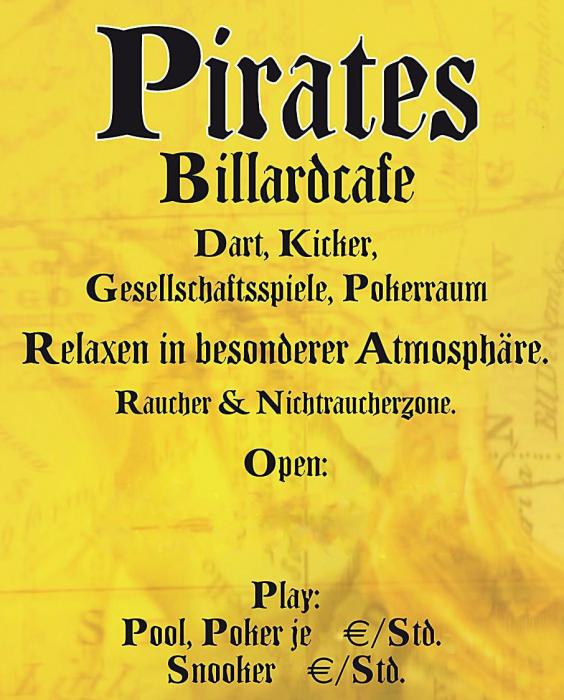
Suche verschörkelte Schriftart -
Habe schon einige Schriftart Seiten ausprobiert,
aber keine konnte genau oder auch nur annähernd
diese Schriftart identifizieren.
Brauche diese um die Getränkekarte umzuändern.
Die Kleinbuchstaben: Ein Freefont namens "BlendfontsMultikultur"
Die Großbuchstaben: Arrus Blk
Du musst nur die beiden verwendeten Schriften trennen, dann werden sie auch erkannt. Also "irates" als das eine Bild und eine Zusammenstellung der Versalien als das andere.
Ich bin Beamter, da ist für mich die amtliche Rechtschreibung bindend.
Würdest Du für amtliche Mitteilungen oder den Dienstgebrauch obiges Schild setzen, wäre Orthographie das letzte, was mir dann noch Sorgen bereiten würde ;) Oder anders: Der Kunde definiert die gültige Orthographie.
Ich finde, es lohnt sich für das & zu kämpfen, um es nicht zur schnöden, bedeutungslosen Abkürzung von "und" verkommen zu lassen.
Üblich ist mittlerweile auch das Weglassen eines Bindestrichs, sei es als Durchkoppelung oder um einen später ergänzten Teil anzuzeigen (Raucher- und Nichtraucherzone). Aber wollen wir das?
sehe ich ähnlich. ich freu mich zwar, wenn laien (=auftraggeber) gerne das „&“ verwenden, ersetze es aber so gut wie immer ungefragt durch „und“. eben weil es die regel gibt. genau so wie ich ziffern 1 bis 12 durch die jeweiligen worte ersetze. es gibt ja auch menschen, die einfach ein „+“ verwenden. die große mehrzahl der keyboard-benutzer will sich einfach das leben einfach machen und so wenig tasten wie möglich drücken.
für detailtypographische schönheiten haben eh die wenigsten was über. wenn ich dann alle heiligen zeiten mal wieder so was feines wie die foundry wilson oder letztens die cala einsetze und mir erlaube, ct-und st-ligaturen zu verwenden, glauben dann gleich alle, dass da wo ein fehler im pdf ist!